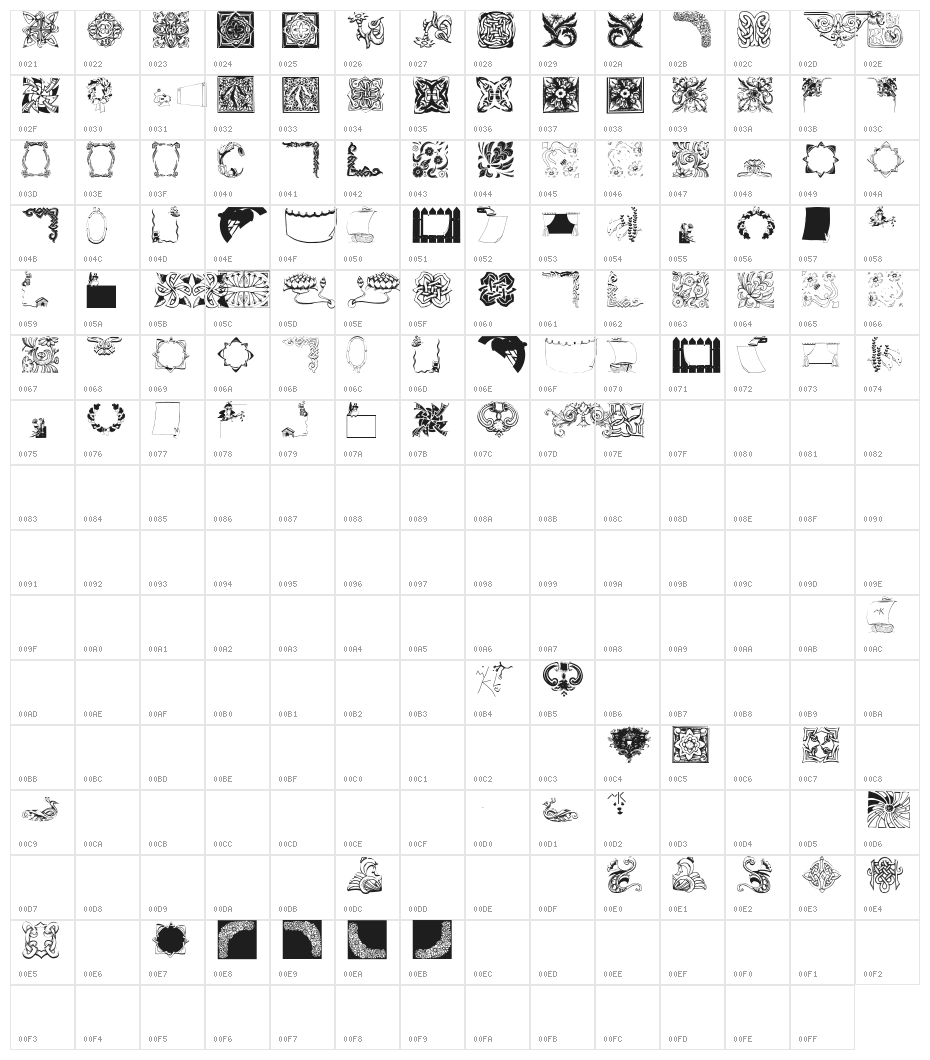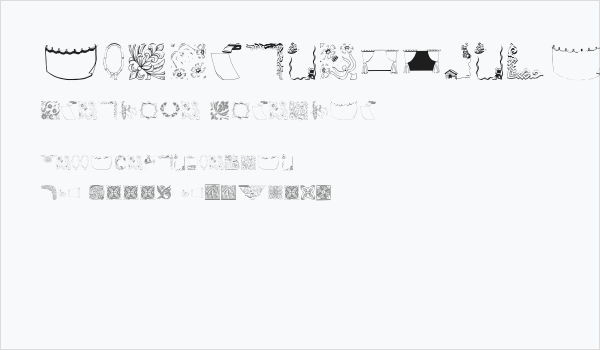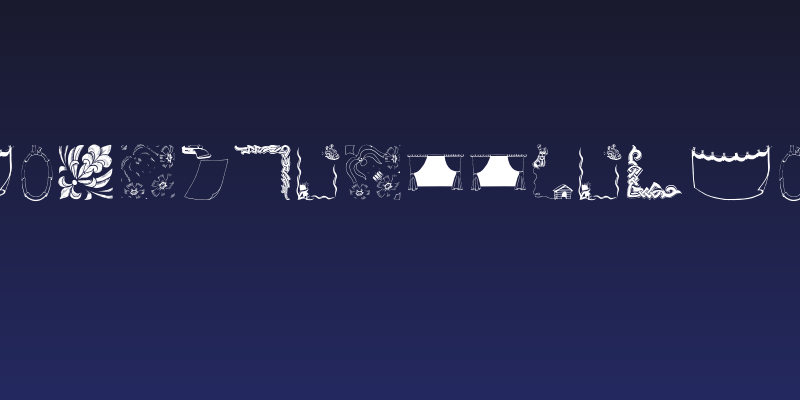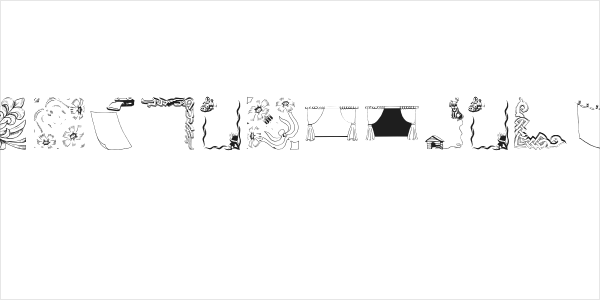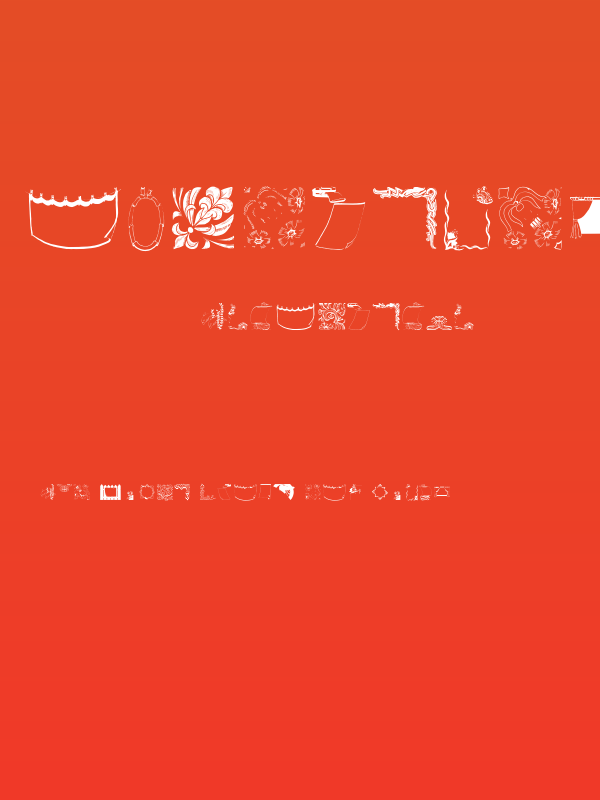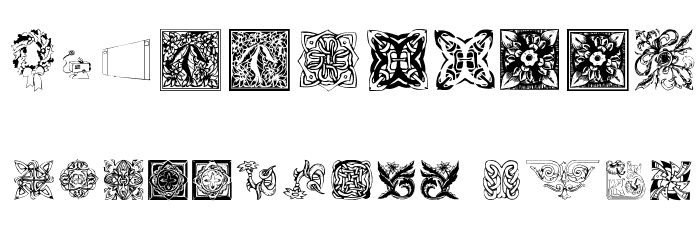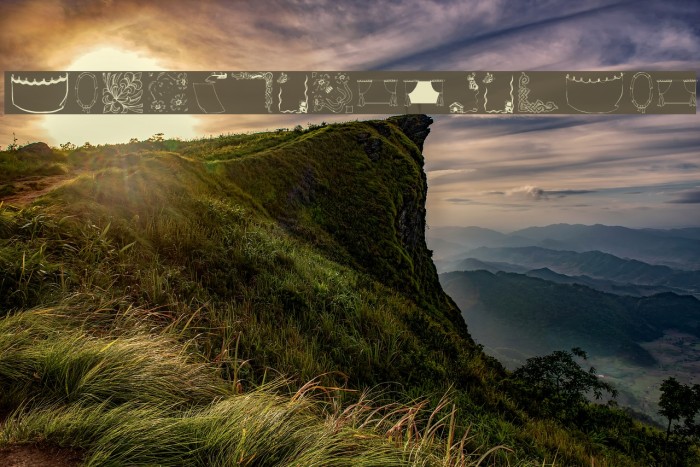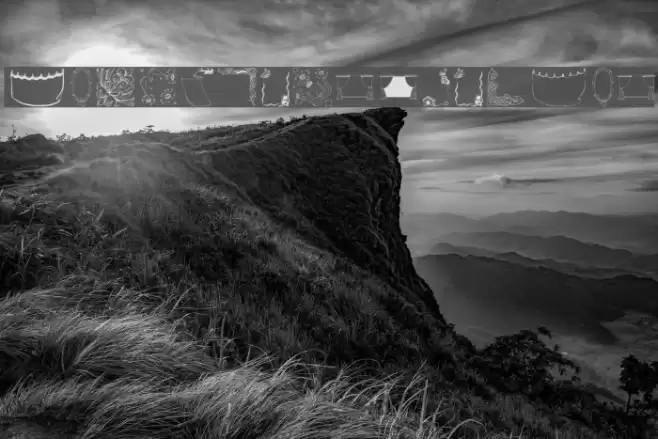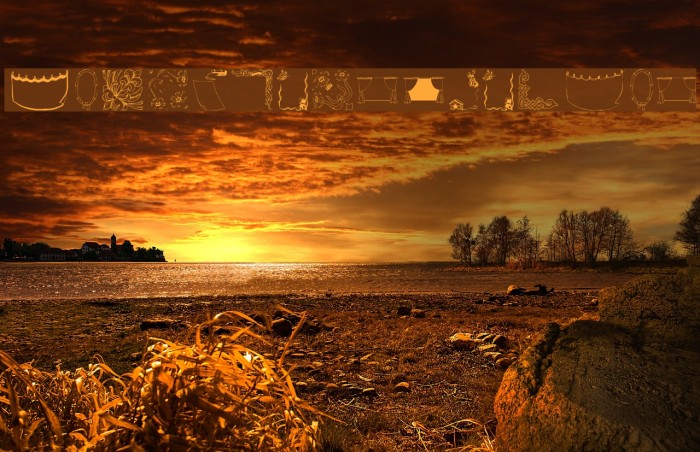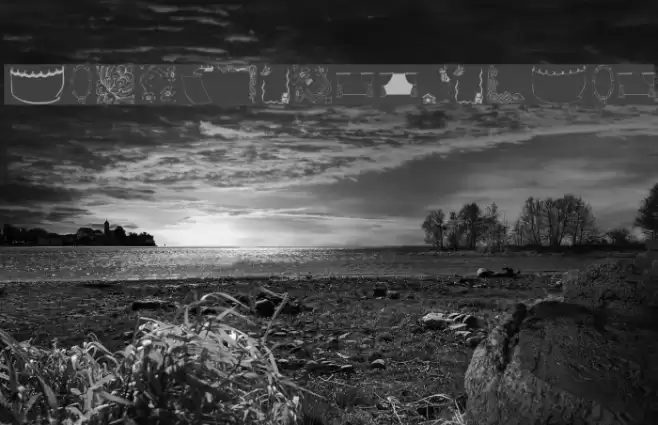
OldFramesSymbols Font
| Categorias | Dingbats |
| Estilo geral | Vintage, Decorative |
| Caso de uso | Borders, Frames, Decorative accents, Logos |
| Projetos propostos | Invitations, certificates, vintage-themed posters, scrapbooking, decorative borders, branding for luxury or heritage products. |